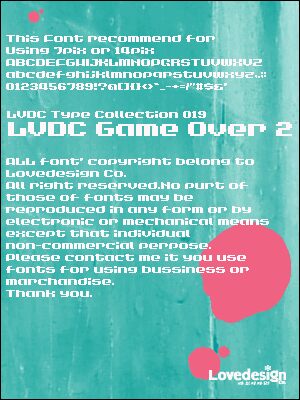
LVDC Game Over 2, autorstwa Wataru Osakabe i Lovedesign co., to darmowy font bitmapowy z charakterystyczną sylwetką arcade „Game Over” oraz wyraźnie schodkowymi formami pikseli. Jego blokowe kształty są pocięte na przejrzyste prostokąty i prześwity, dzięki czemu krój wygląda jak tytuł wyjęty prosto z ekranu gry o niskiej rozdzielczości.
LVDC Game Over 2 świetnie pasuje do menu gier, plakatów arcade, grafiki tablic wyników, nakładek streamingowych i nagłówków wydarzeń gamingowych, gdzie sztywny pikselowy rytm wykonuje całą pracę wizualną. Ta geometria o niskiej rozdzielczości nadaje każdemu projektowi klimat arcade bez potrzeby dodawania zbędnych dekoracji.